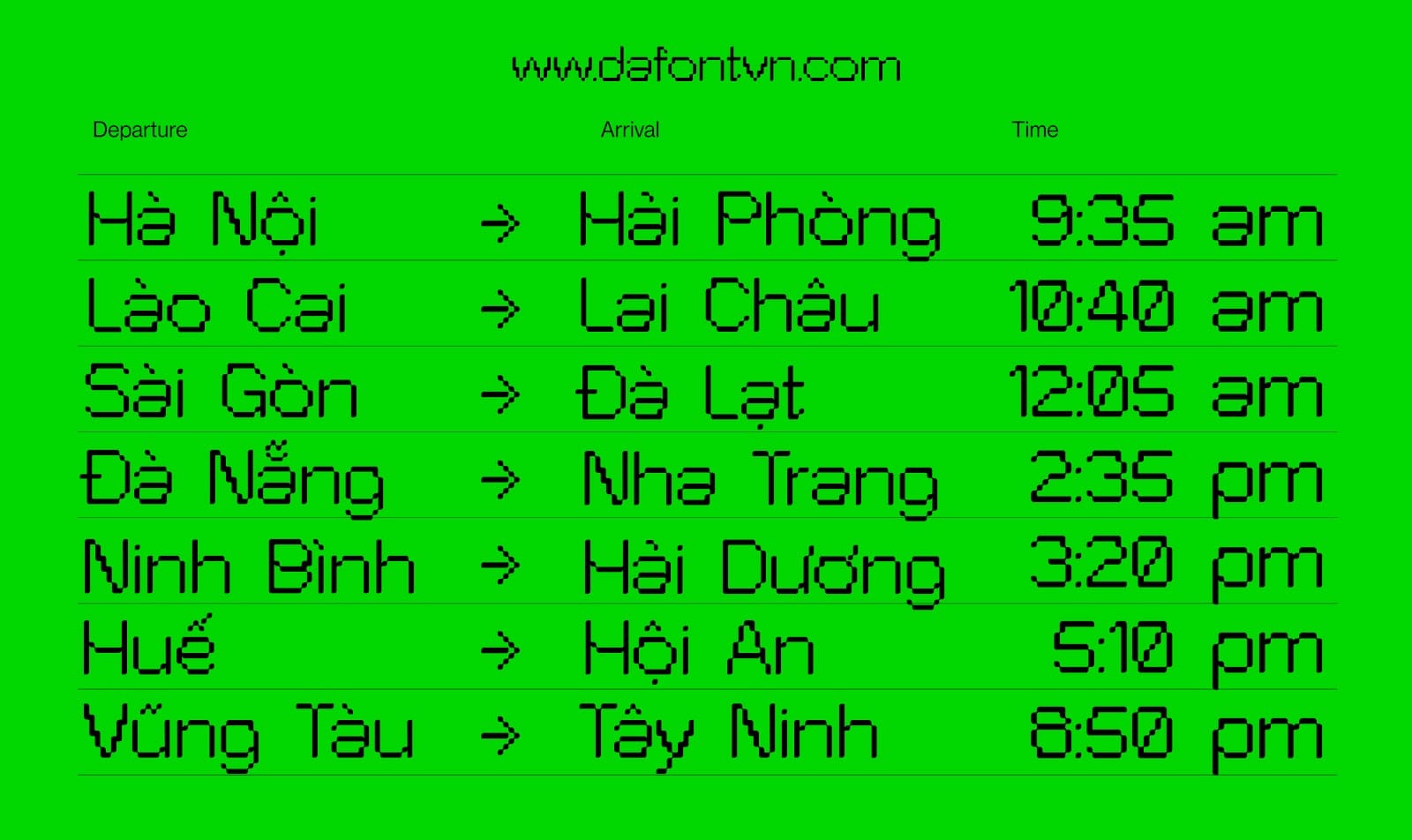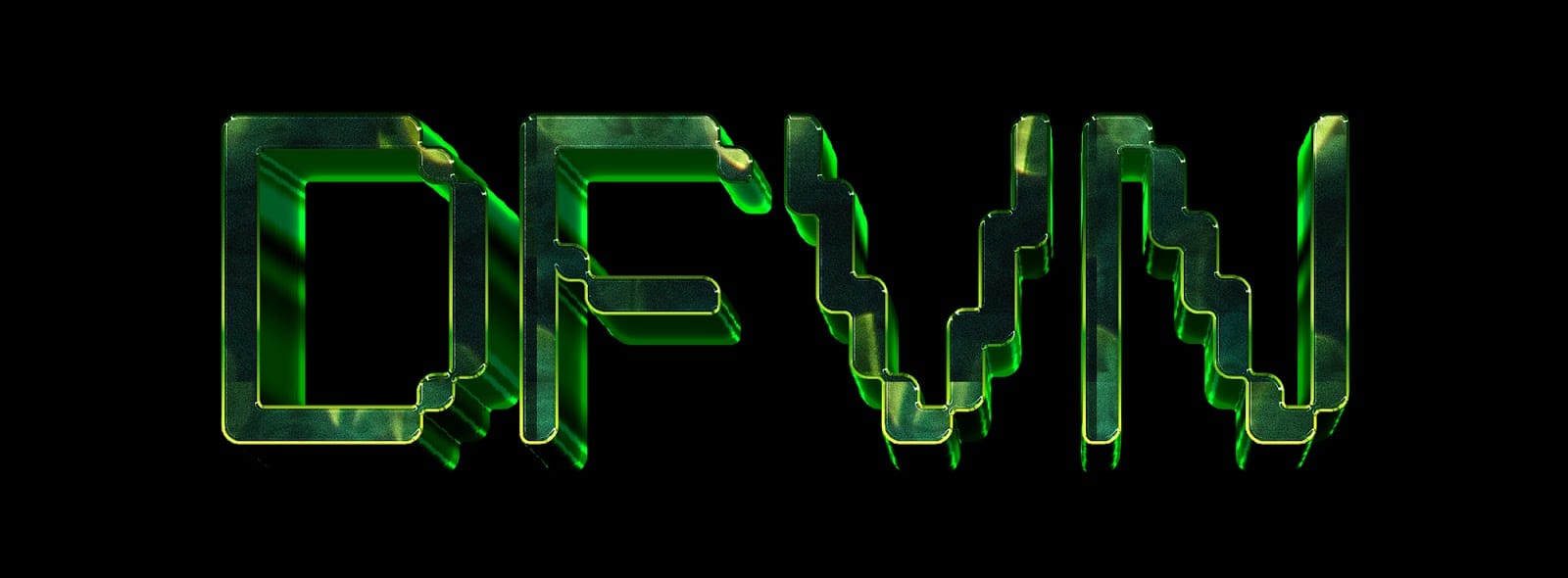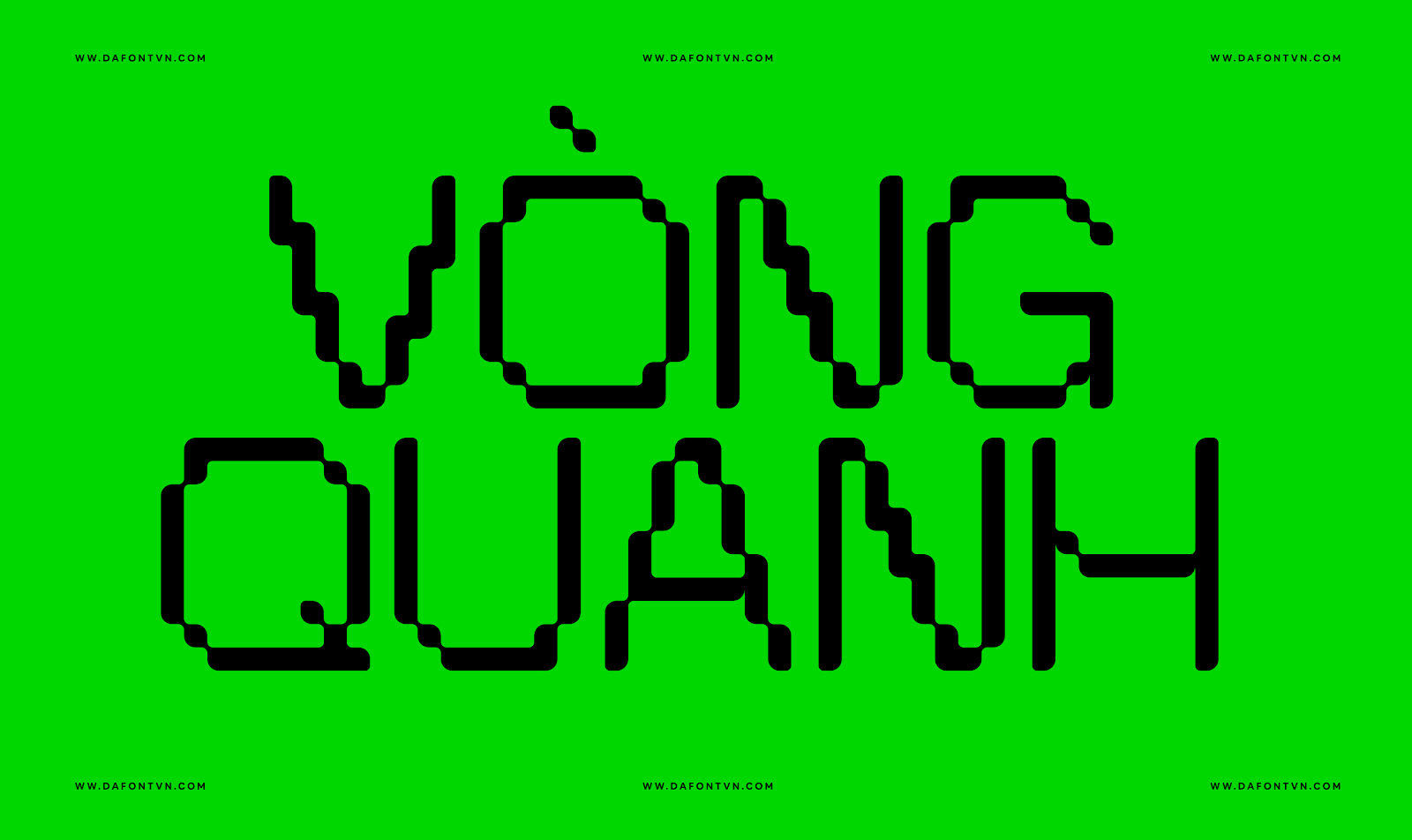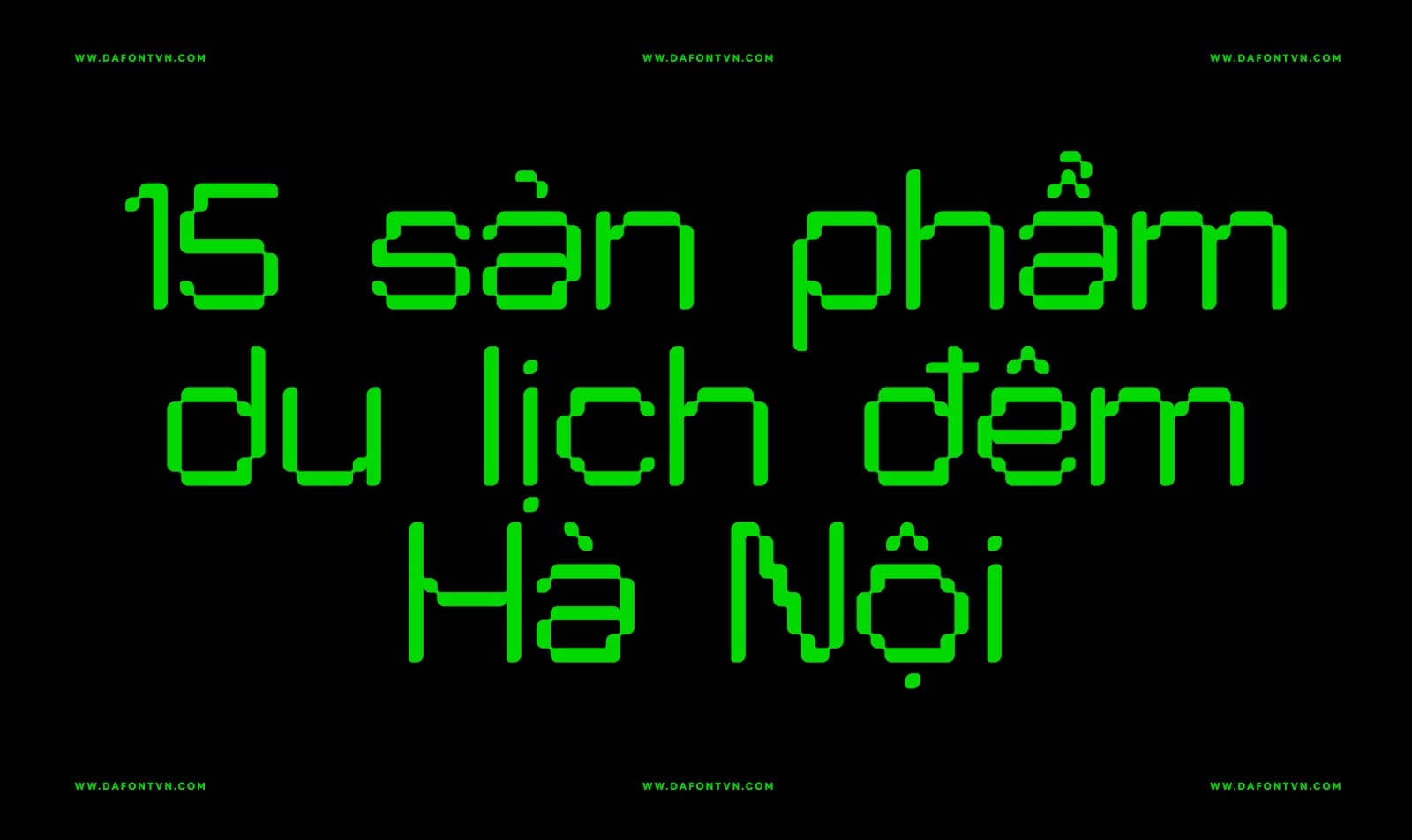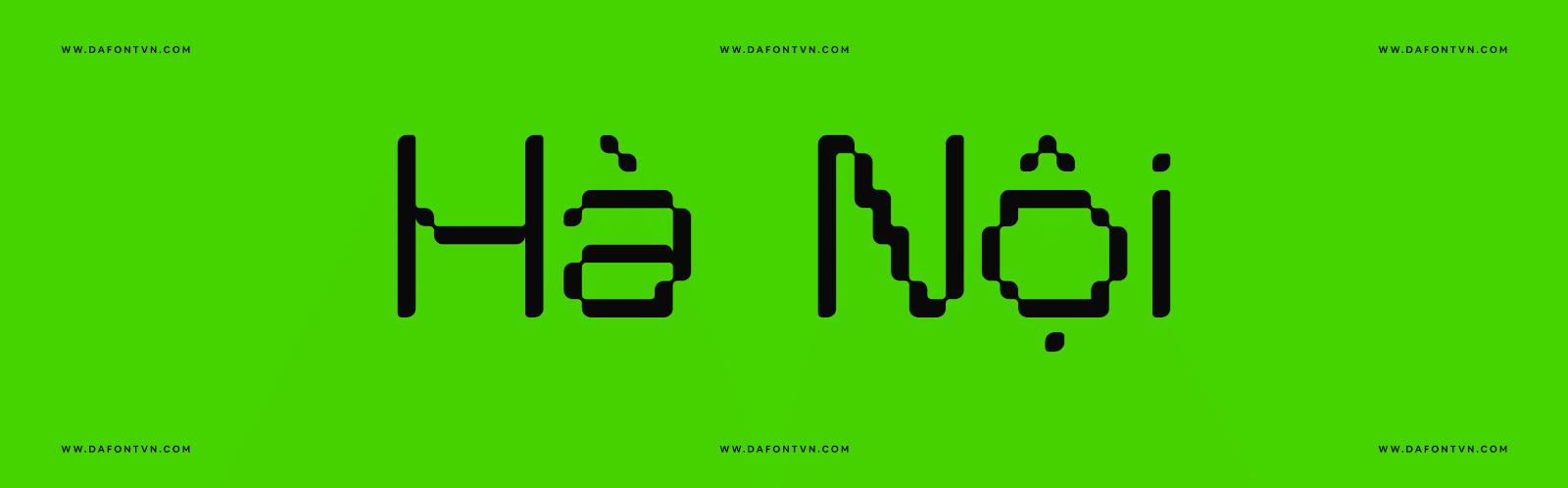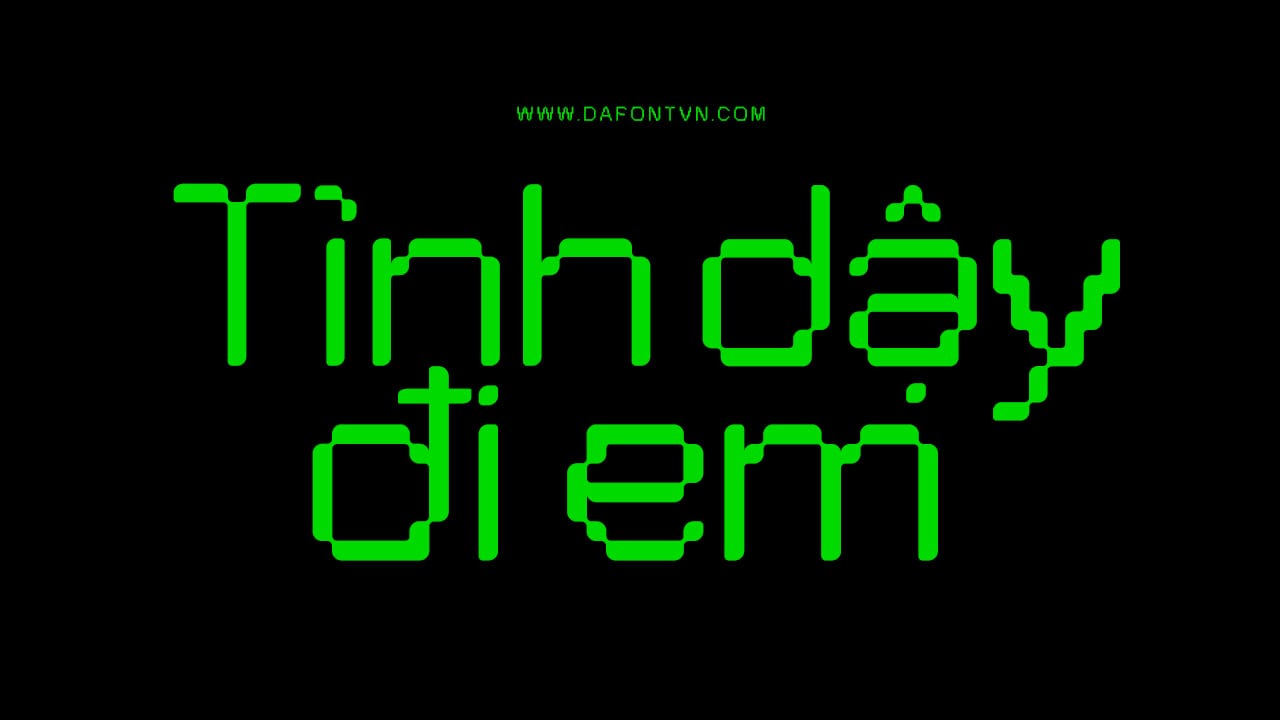
Pexel Grotesk được ra đời giống như hầu hết các phông chữ với hình dạng và chữ cái. Ý tưởng là tạo ra một font pixel đẹp mắt.
Trên internet, khó khăn để tìm thấy một kiểu chữ pixel với tỷ lệ phù hợp và có thứ gì đó giúp phân biệt nó với với hình dạng pixel và khối.
Pexel Grotesk dựa trên kích thước và tỷ lệ của một kiểu chữ grotesque trong khi vẫn nằm trong vị trí lưới (grid).
Một số chữ cái không được thiết kế theo đúng nghĩa là cần phải được xây dựng như một font pixel. Điều này giúp cho kiểu chữ trở nên khác biệt nhưng đồng thời cũng nhất quán.
Độ tròn trịa ở các cạnh, mặc dù có thể nghe như một từ tưởng tượng cho một kiểu chữ pixel, nhưng lại mang lại hình dạng thú vị, đặc biệt là khi sử dụng ở kích thước lớn.
Đây có thể nói là một font pixel tuyệt vời mà mình rất thích nên đã việt hóa nó, Pexel Grotesk phù hợp cho nhiều mục đích thiết kế khác nhau.